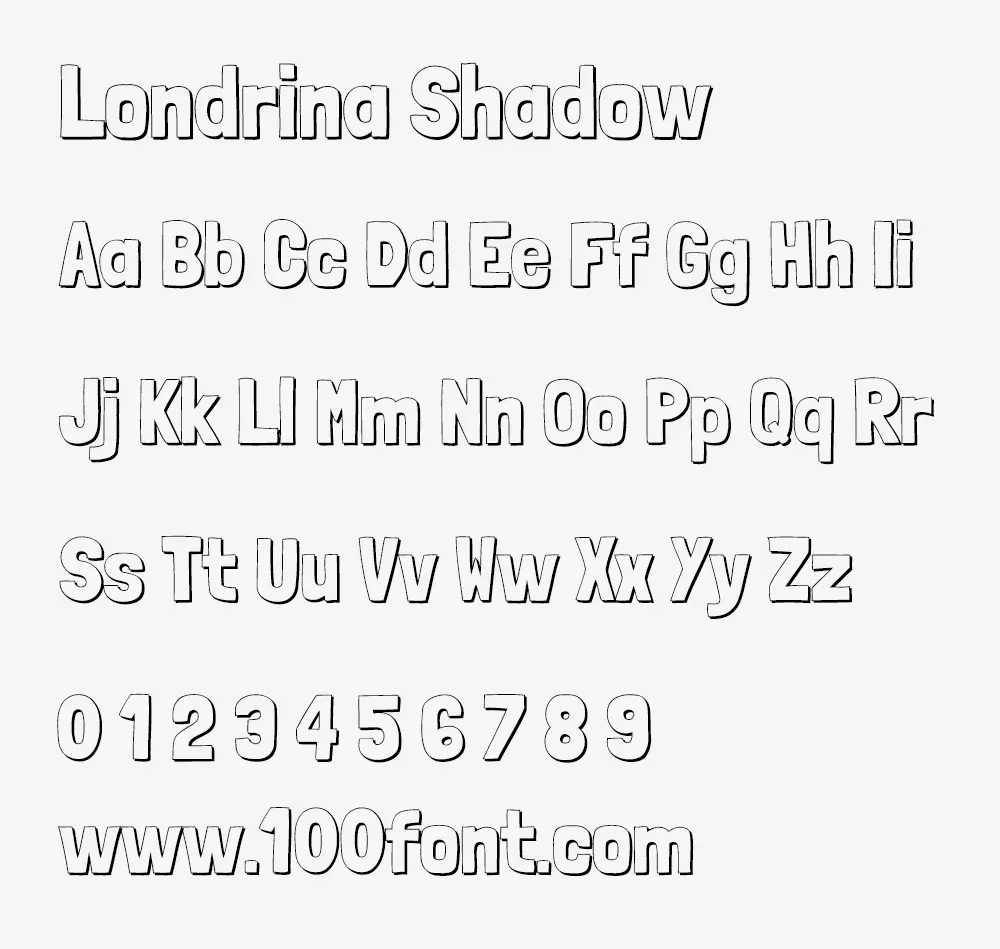
Londrina是一種由在方形紙上手動繪製的字母製成的字體,然後在描圖紙上重新繪製。我們的出發點是畫一個通用的無襯線風格的字體,就像我們在自助餐廳和街頭商業中經常看到的字母一樣,不僅在巴西。Londrina現在分為三種不同的包裝,固體包裝、圖層包裝和SVG彩色包裝。起初,Londrina被稱為Folk,但這個名字已經由另一家鑄造廠註冊,隨著Londrina加入谷歌字體目錄,我們認為是時候取一個新名字了,向我居住的城市致敬。自從我開始發行這個字體以來,我已經在各種專業和業餘項目中看到了Londrina的展示,它一炮而紅,是初學者運氣的典範。
Londrina is a typeface made from letters manually drawn on squared paper and then retraced on tracing paper. The starting point was to draw a generic sans serif vernacular-inspired type like the letters we see all the time in cafeterias and street commerce not only in Brazil. Londrina is now being distributed in 3 different packs, The Solid pack, The Layer pack and The SVG Color pack. Originally Londrina was called Folk, but the name was already had registered by another foundry and as Londrina was join the Google Fonts catalog, we thought it was time for a new name, a tribute to the city where I lived. Since I started distributing this Font I have seen Londrina displayed in all sorts of professional and amateur projects, an instant hit and a great exemple of beginner's luck.